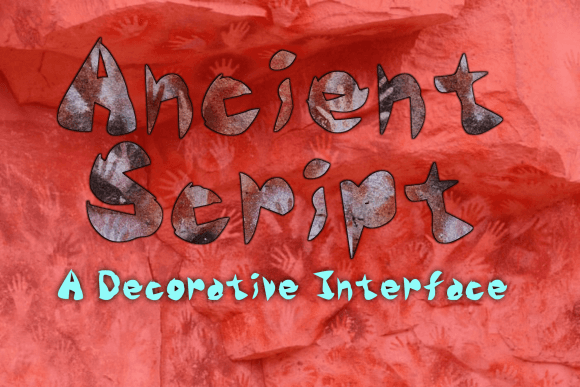
Fonte de escrita antiga para identidade visual feminina e gráficos para redes sociais.
Ancient Script é uma fonte cursiva elegante, criada para identidade visual sofisticada, logotipos estilosos e visuais de mídias sociais com design impecável. Suas curvas refinadas e fluidez natural a tornam ideal para uma estética feminina e apresentações exclusivas.
Esta fonte confere um toque artesanal e sofisticado a cada design. Seja em assinaturas, embalagens de produtos de beleza ou sobreposições de citações, a Ancient Script oferece charme atemporal e fluidez visual.
Com formas de letras equilibradas e alta legibilidade, apresenta um excelente desempenho em formatos digitais e impressos, conferindo elegância pessoal a cada projeto.
O que você pode fazer
- Logotipos e kits de marca elegantes
- Embalagem e rótulos do produto
- Frases e capas para destaques do Instagram
- Convites e artigos de papelaria para casamento
- Gráficos promocionais e livros eletrônicos
Por que você vai adorar
- Elegância manuscrita com um toque feminino
- Ideal para identidade visual e conteúdo para redes sociais.
- Fluxo limpo e espaçamento suave entre as letras.
- Ideal para projetos de design sofisticados.
P: Qual é o estilo da escrita antiga?
A: Ancient Script é uma fonte de caligrafia moderna com traços suaves e elegantes, criada para marcas de luxo e femininas.
P: Posso usar isso para imagens em redes sociais?
A: Sim, é perfeito para citações do Instagram, pins do Pinterest, destaques de stories e outros conteúdos visuais.
P: Posso usar escrita antiga em materiais impressos?
A: Com certeza. É ideal para artigos de papelaria, embalagens, etiquetas e materiais impressos que exigem uma estética elegante.